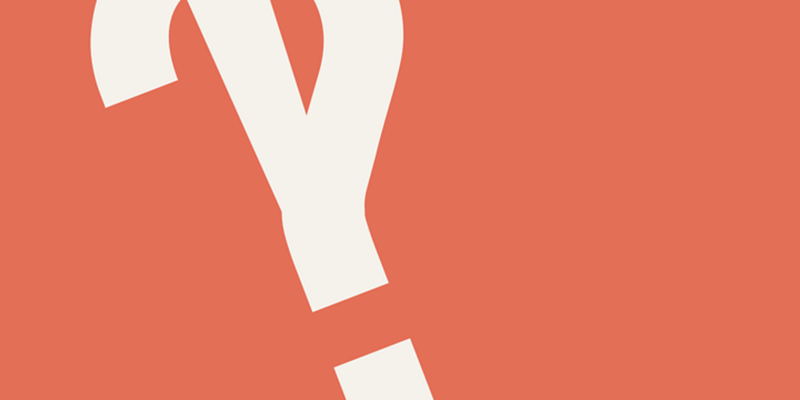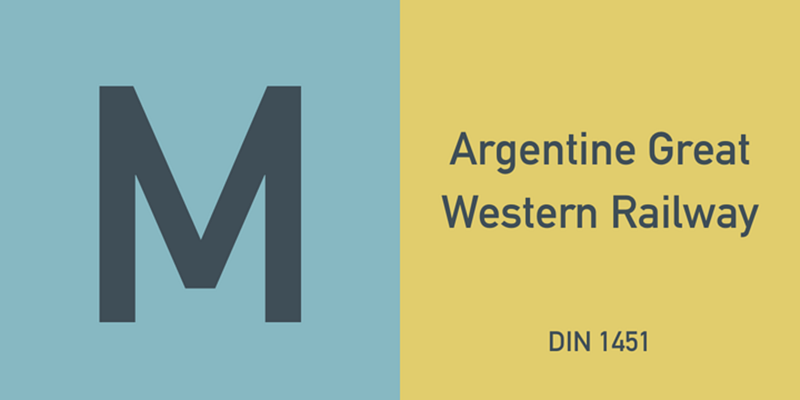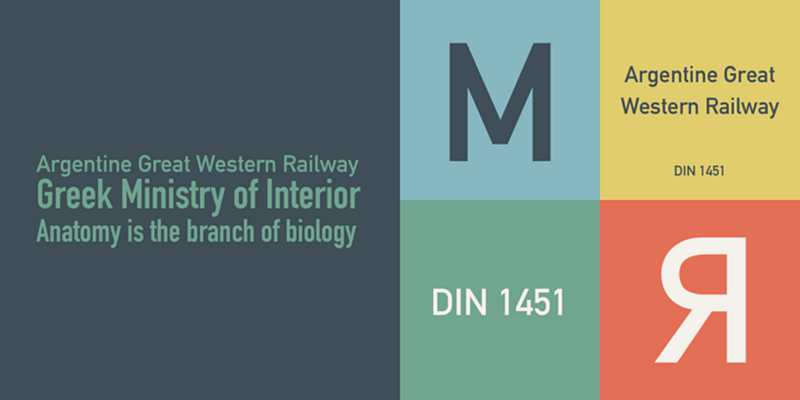
DIN sta per Deutsche Industrienorm, standard industriale tedesco. Nel 1936, il Comitato Standard Tedesco scelse il DIN 1451 come font standard per i settori della tecnologia, del traffico, dell’amministrazione e degli affari. Il comitato scelse un font sans serif per la sua leggibilità e le forme di facile scrittura. Questo font non è stato utilizzato nelle pubblicità e in altri usi artistici, e ci sono state divergenze sulle sue qualità estetiche. Ciononostante, questo font si vedeva ovunque nelle città tedesche e nei segnali stradali e quindi è entrato nelle pubblicità per la sua facilità di riconoscimento.